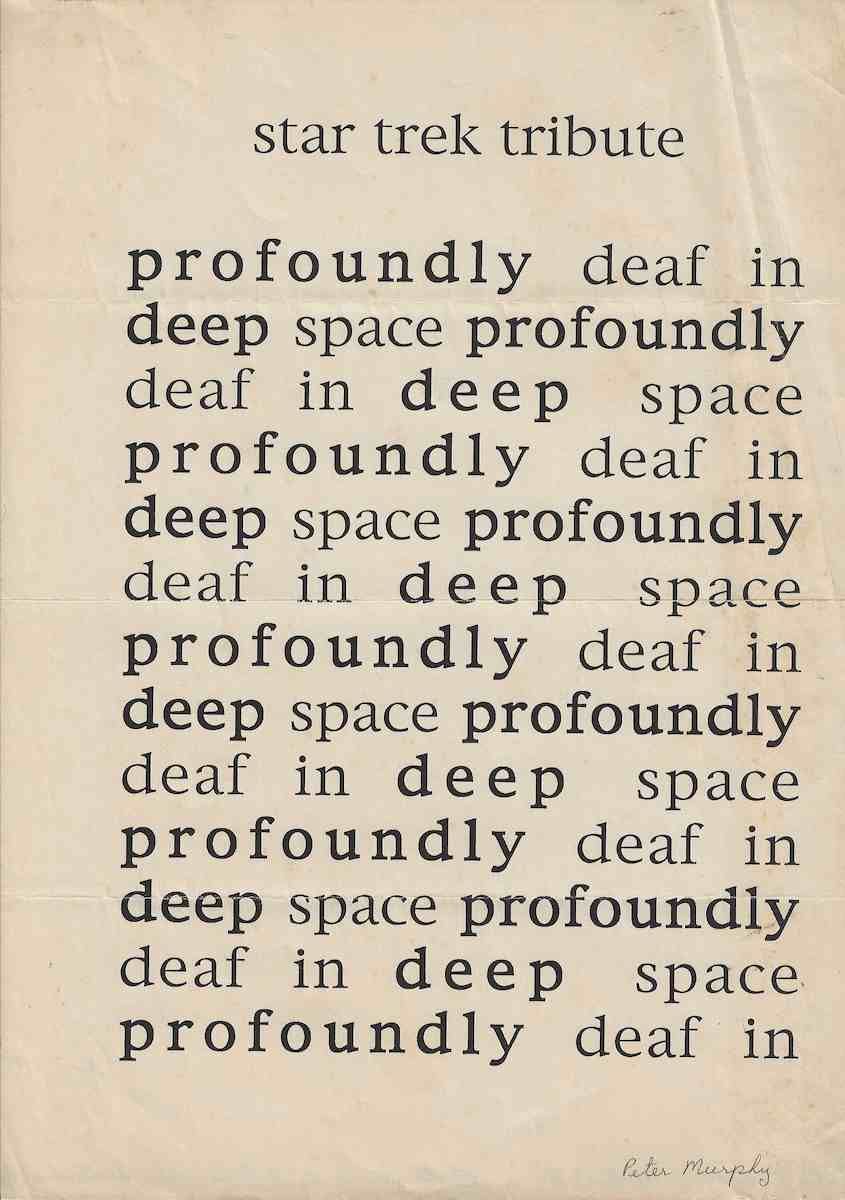
Star Trek Tribute é uma poesia visual original do artista, poeta concreto e escritor australiano Peter Murphy, 1945 a 2024, produzida no contexto de sua pesquisa com poesia concreta, poesia visual, tipografia e experimentação verbal.
Star Trek Tribute é uma poesia visual original do artista, poeta concreto e escritor australiano Peter Murphy, 1945 a 2024, produzida no contexto de sua pesquisa com poesia concreta, poesia visual, tipografia e experimentação verbal. A obra utiliza exclusivamente linguagem textual e organização espacial para transformar uma frase repetida em composição gráfica, sonora e semântica. O documento conserva ainda a assinatura manuscrita de Peter Murphy e, no verso, seu endereço em Eaglemont, Victoria, Austrália, constituindo importante fonte primária para identificação, proveniência e localização do artista.O título Star Trek Tribute aparece centralizado na parte superior da folha. A referência a Star Trek insere a obra no universo da ficção científica e da cultura popular, mas Murphy desloca essa referência para um procedimento poético construído por repetição, ritmo e organização tipográfica. Em vez de representar visualmente personagens ou imagens da série, o artista cria uma experiência baseada na linguagem e na ideia de espaço profundo.A composição é construída pela repetição das palavras profoundly deaf in deep space. A sequência é distribuída em várias linhas e reorganizada continuamente ao longo da página. Em determinados momentos, a frase parece completar se e em seguida reiniciar, produzindo uma estrutura circular e acumulativa. A disposição transforma a leitura convencional em percurso visual.A expressão profoundly deaf in deep space pode ser compreendida como profundamente surdo no espaço profundo. O emprego reiterado de deep space estabelece associação direta com o universo de Star Trek, enquanto profoundly deaf introduz uma situação paradoxal relacionada ao silêncio, ausência de som, isolamento e comunicação no espaço. Essa relação entre som e silêncio é especialmente significativa dentro da produção de Peter Murphy, que trabalhou tanto com poesia concreta e visual quanto com as possibilidades sonoras da palavra.O poema estabelece assim uma tensão entre profundidade espacial e impossibilidade auditiva. A palavra deep aparece repetidamente associada a profoundly, enquanto deaf interrompe e reorganiza a sequência verbal. A construção pode ser lida simultaneamente como frase, padrão tipográfico, estrutura visual e sequência rítmica.A repetição não é meramente decorativa. Cada linha modifica a percepção das anteriores e transforma palavras comuns em unidades gráficas. O espaçamento amplo entre determinadas palavras e a regularidade da tipografia criam campos vazios que passam a participar da composição. Esses intervalos funcionam como pausas visuais e sugerem distância, isolamento e extensão espacial.A estrutura da obra aproxima se diretamente dos princípios da poesia concreta, na qual a posição das palavras na página participa da produção de significado. O poema não depende apenas da interpretação lexical da frase. Forma, repetição, intervalo, alinhamento, ritmo e ocupação do espaço branco constituem elementos essenciais da obra.Esse procedimento corresponde à trajetória conhecida de Peter Murphy na poesia concreta australiana. Murphy desenvolveu desde a década de 1970 trabalhos nos quais palavras, letras, símbolos e configurações espaciais eram utilizados como matéria visual. Sua produção integra a história da poesia concreta e visual australiana ao lado de artistas e poetas como Sweeney Reed, Alan Riddell, Alex Selenitsch, Jas H. Duke,
O, Richard Tipping, TT.O e outros participantes desse ambiente experimental.A National Library of Australia preserva Seen and Unseen, concrete poems, publicação de Peter Murphy realizada em edição limitada de 300 exemplares assinados e numerados na década de 1970. O registro confirma documentalmente a atuação do artista no campo da poesia concreta australiana. (catalogue.nla.gov.au)Murphy também refletiu teoricamente sobre essa linguagem. Em 1977 publicou Concrete Poetry: A Form In Search of Its Selves em Australian Literary Studies, texto no qual discutiu a poesia concreta e sua própria posição dentro do campo experimental australiano. (australianliterarystudies.com.au)Star Trek Tribute deve ser compreendida dentro desse contexto. O trabalho utiliza uma referência amplamente reconhecível da cultura de massa para produzir uma experiência poética baseada em linguagem mínima, serialidade e espacialização. Essa estratégia aproxima poesia concreta, poesia visual, cultura popular e experimentação conceitual.Na extremidade inferior direita da frente encontra se a assinatura manuscrita Peter Murphy. A assinatura possui grande importância documental, pois confirma a autoria material do exemplar e diferencia este Peter Murphy australiano de diversos homônimos existentes em outros campos artísticos.O verso da obra apresenta informação manuscrita de proveniência e contato. É possível ler Peter Murphy, 3 The Panorama, Eaglemont, Victoria, 3084, Australia. O endereço relaciona diretamente a obra ao artista em Eaglemont, subúrbio de Melbourne, no estado de Victoria. Essa informação coincide com registros posteriores que também relacionam Peter Murphy a Eaglemont e à região de Banyule.A presença do endereço transforma o documento em evidência particularmente valiosa para a história das redes de correspondência artística. Obras de poesia visual em folhas avulsas, cartões, envelopes e pequenos impressos circularam intensamente através do correio entre participantes das redes internacionais de poesia visual e mail art.No contexto do acervo relacionado a J. Medeiros, a peça adquire uma dimensão adicional. A existência de uma obra original de Peter Murphy contendo sua identificação e endereço australiano dentro de um conjunto relacionado às redes brasileiras de arte postal fornece evidência material da circulação internacional da poesia visual australiana. Quando a proveniência específica de envio ou recebimento por J. Medeiros estiver documentalmente estabelecida pelo conjunto arquivístico, essa conexão deverá ser registrada como correspondência artística direta.Peter Murphy é documentado historicamente não apenas como poeta concreto mas também em contextos relacionados à poesia visual e mail art australiana. A circulação postal de poemas visuais permitia estabelecer contatos internacionais fora dos sistemas tradicionais de galerias e editoras, aproximando artistas da Austrália, Europa, América Latina e outros territórios.Não há indicação de que Star Trek Tribute pertença ao movimento brasileiro Poema Processo nem evidência de que Peter Murphy tenha integrado formalmente esse movimento. Entretanto, a obra apresenta afinidades evidentes com questões centrais da poesia experimental internacional, especialmente utilização espacial da palavra, repetição, serialidade, comunicação visual e transformação do texto em estrutura gráfica.Star Trek Tribute constitui, portanto, importante documento da produção de Peter Murphy e da poesia visual australiana. A obra estabelece relações semânticas entre Peter Murphy, Austrália, Eaglemont, Victoria, Melbourne, poesia concreta, poesia visual, experimental poetry, concrete poetry, mail art, arte postal, Star Trek, ficção científica, cultura popular, linguagem, tipografia, repetição, espaço e comunicação. Sua assinatura e endereço manuscrito reforçam seu valor como documento original, fonte de proveniência e testemunho das redes internacionais de circulação artística.TEXT FOR THE SALSA PROGRAM IN ENGLISHStar Trek Tribute is an original visual poem by the Australian concrete poet, visual poet and writer Peter Murphy, 1945 to 2024, produced within his broader investigation of concrete poetry, visual poetry, typography and experimental language. The work uses exclusively textual language and spatial organization to transform a repeated phrase into a graphic, sonic and semantic composition. The document also retains the handwritten signature of Peter Murphy and, on the reverse, his address in Eaglemont, Victoria, Australia, providing important primary evidence for authorship, provenance and the geographical location of the artist.The title Star Trek Tribute is centered at the top of the sheet. The reference to Star Trek introduces the work into the field of science fiction and popular culture, but Murphy transforms that cultural reference through a poetic procedure based on repetition, rhythm and typographic organization. Rather than representing characters or imagery from the television series, the artist constructs an experience through language and the concept of deep space.The composition is built from repeated occurrences of the words profoundly deaf in deep space. The sequence is distributed across several lines and continuously reorganized down the page. At certain points the sentence seems to reach completion before beginning again, creating a circular and cumulative structure. Its arrangement transforms conventional reading into a visual trajectory.The expression profoundly deaf in deep space establishes a paradox involving silence, the absence of sound, isolation and communication within outer space. The repeated use of deep space creates the most direct semantic relationship with Star Trek, while profoundly deaf introduces a condition of extreme auditory absence.This relationship between sound and silence is particularly relevant to the practice of Peter Murphy, who explored not only concrete and visual poetry but also the sonic possibilities of words. The poem therefore establishes a tension between spatial depth and the impossibility of hearing.Repetition is not simply decorative. Each line alters the perception of those before it and turns ordinary words into graphic units. The generous spaces between particular words and the regularity of the typography create areas of emptiness that become active components of the composition. These intervals function as visual pauses and suggest distance, isolation and spatial extension.The structure corresponds directly with the principles of concrete poetry, in which the placement of language on the page participates in producing meaning. The poem does not depend exclusively upon the lexical meaning of the sentence. Form, repetition, interval, alignment, rhythm and the occupation of white space are essential components of the work.This procedure corresponds with Murphy's documented place in Australian concrete poetry. From the 1970s onward he developed works in which words, letters, symbols and spatial configurations functioned as visual material. His practice belongs to the history of Australian concrete and visual poetry alongside figures including Sweeney Reed, Alan Riddell, Alex Selenitsch, Jas H. Duke,
O, Richard Tipping and TT.O.The National Library of Australia preserves Seen and Unseen, concrete poems, a publication by Peter Murphy issued in a limited edition of 300 signed and numbered copies during the 1970s. The bibliographical record provides direct documentation of his activity within Australian concrete poetry. (catalogue.nla.gov.au)Murphy also reflected theoretically on the medium. In 1977 he published Concrete Poetry: A Form In Search of Its Selves in Australian Literary Studies, discussing concrete poetry and his own position within Australian experimental writing. (australianliterarystudies.com.au)Star Trek Tribute should be understood within this context. It uses a widely recognizable reference from mass culture to construct a poetic experience based on minimal language, serial repetition and spatial organization. The work therefore brings together concrete poetry, visual poetry, popular culture and conceptual experimentation.The lower right corner of the front bears the handwritten signature Peter Murphy. This signature is significant documentary evidence because it confirms the authorship of this particular object and helps distinguish the Australian artist from several other individuals of the same name.The reverse contains handwritten provenance and contact information. It reads Peter Murphy, 3 The Panorama, Eaglemont, Victoria, 3084, Australia. The address directly associates the work with the artist in Eaglemont, a suburb of Melbourne in the state of Victoria. This information is consistent with later documentation connecting Murphy with Eaglemont and the Banyule area.The presence of the address makes the document particularly valuable for understanding correspondence networks. Visual poems on individual sheets, cards, envelopes and small printed works frequently circulated through the postal system among participants in international visual poetry and mail art networks.Within an archival context connected with J. Medeiros, the work acquires an additional historical dimension. An original Peter Murphy visual poem carrying his Australian address within a collection related to Brazilian postal art provides material evidence of the international circulation of Australian visual poetry. When direct sending or receipt by J. Medeiros is established through the archival provenance of the object, that relationship should be catalogued as direct artists correspondence.Peter Murphy is historically documented not only as a concrete poet but also within contexts associated with Australian visual poetry and mail art. Postal circulation of visual poems allowed international contacts to develop beyond conventional systems of galleries and publishing houses, linking artists in Australia with participants in Europe, Latin America and elsewhere.There is no indication that Star Trek Tribute belonged to the Brazilian Process Poem Movement, nor evidence that Peter Murphy formally participated in that movement. The work nevertheless has clear affinities with international experimental poetry, particularly through its spatial use of language, repetition, seriality, visual communication and transformation of text into graphic structure.Star Trek Tribute is therefore an important document of the practice of Peter Murphy and Australian visual poetry. It establishes semantic relationships among Peter Murphy, Australia, Eaglemont, Victoria, Melbourne, concrete poetry, visual poetry, experimental poetry, mail art, postal art, Star Trek, science fiction, popular culture, language, typography, repetition, space and communication. Its handwritten signature and address reinforce its importance as an original document, provenance source and record of international artistic circulation.
Poesia visual original intitulada Star Trek Tribute, do poeta e artista australiano Peter Murphy, 1945 a 2024. A composição utiliza repetidamente as palavras profoundly deaf in deep space, organizadas em sucessivas linhas tipográficas que transformam a frase em estrutura visual, rítmica e espacial. O título estabelece referência direta ao universo de Star Trek e à ficção científica, enquanto a repetição de deep space e profoundly deaf cria uma relação conceitual entre espaço profundo, silêncio, audição, isolamento e comunicação. A obra apresenta assinatura manuscrita de Peter Murphy na frente. No verso encontra se sua identificação acompanhada pelo endereço 3 The Panorama, Eaglemont, Victoria, 3084, Australia, informação de grande importância para proveniência e para a documentação de sua atividade na região de Melbourne. O trabalho relaciona se diretamente à trajetória de Murphy na poesia concreta e poesia visual australiana e possui relevância para o estudo da circulação internacional de poesia experimental e mail art.OBSERVATION TEXT IN ENGLISHOriginal visual poem titled Star Trek Tribute by the Australian poet and artist Peter Murphy, 1945 to 2024. The composition repeatedly uses the words profoundly deaf in deep space, arranged in successive typographic lines that transform the sentence into a visual, rhythmic and spatial structure. The title establishes a direct reference to Star Trek and science fiction, while the repetition of deep space and profoundly deaf creates a conceptual relationship involving outer space, silence, hearing, isolation and communication. The work bears the handwritten signature of Peter Murphy on the front. The reverse contains his identification and the address 3 The Panorama, Eaglemont, Victoria, 3084, Australia, providing important evidence for provenance and for documenting his activity in the Melbourne region. The work relates directly to Murphy's practice in Australian concrete and visual poetry and is relevant to the study of the international circulation of experimental poetry and mail art.
Star Trek Tribute is an original visual poem by the Australian concrete poet, visual poet and writer Peter Murphy, 1945 to 2024, produced within his broader investigation of concrete poetry, visual poetry, typography and experimental language.